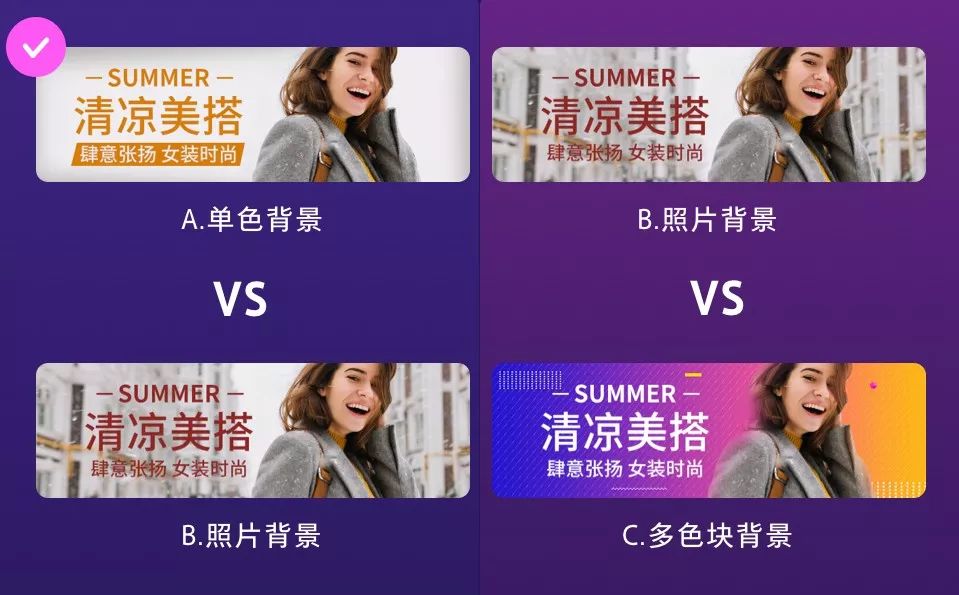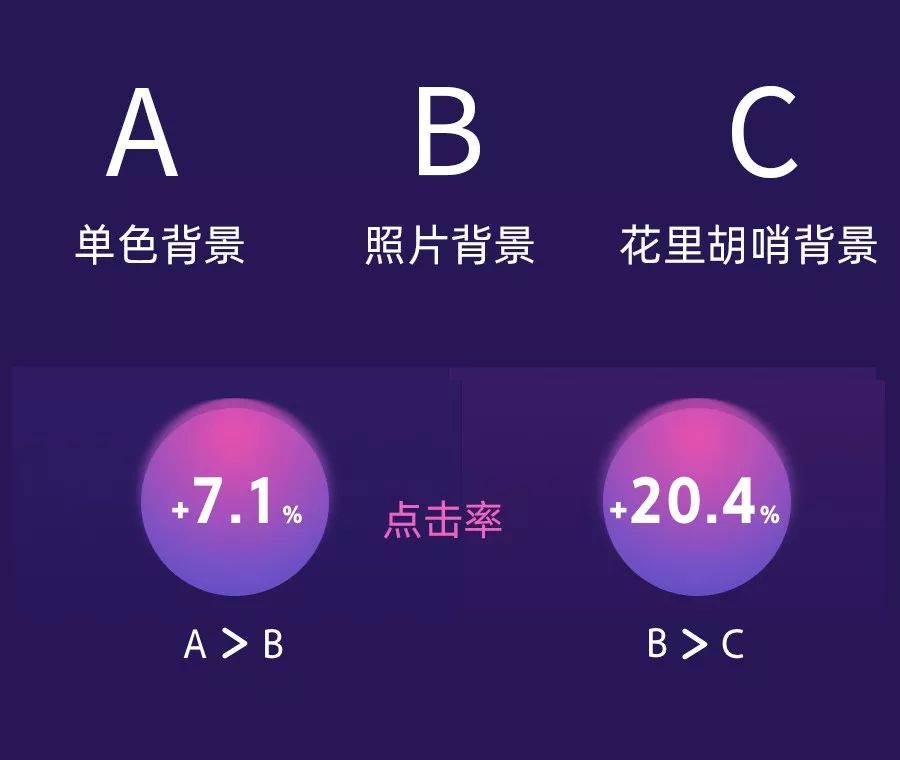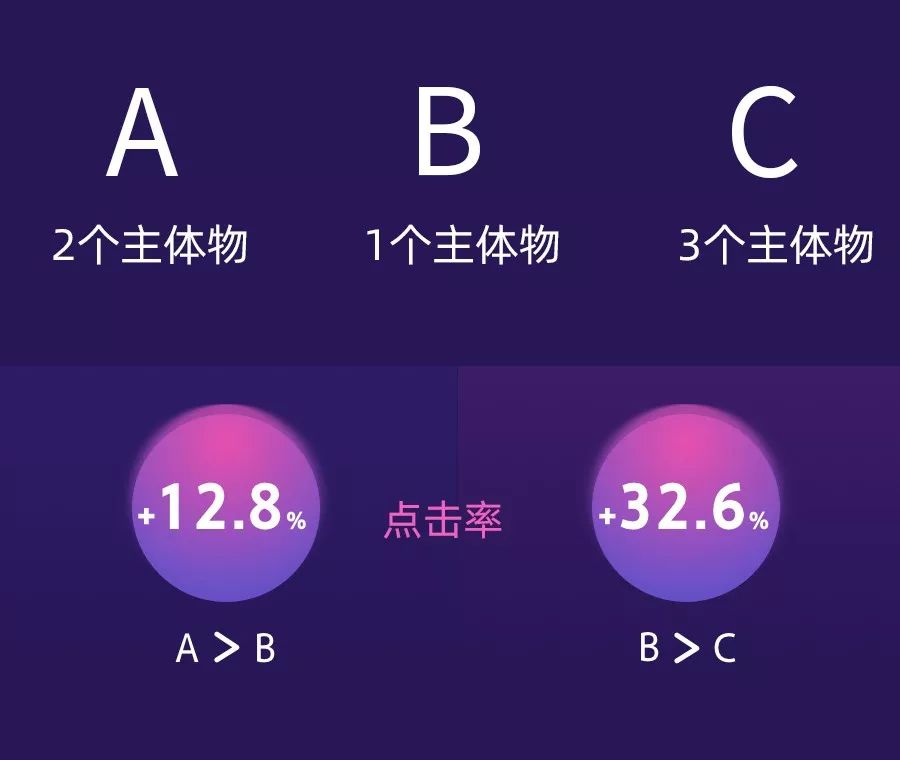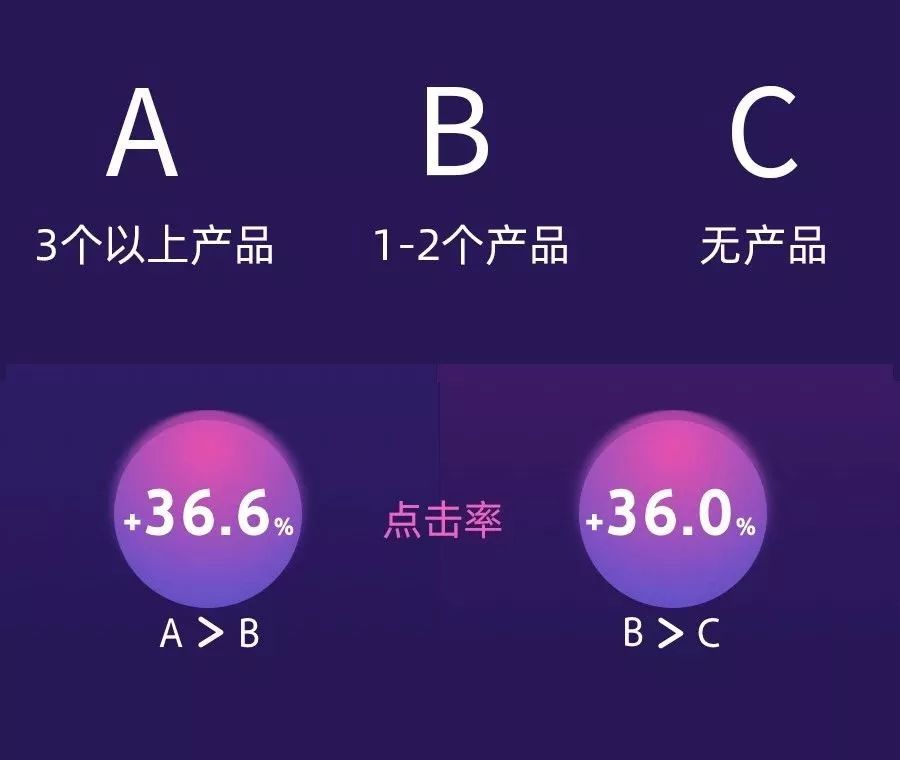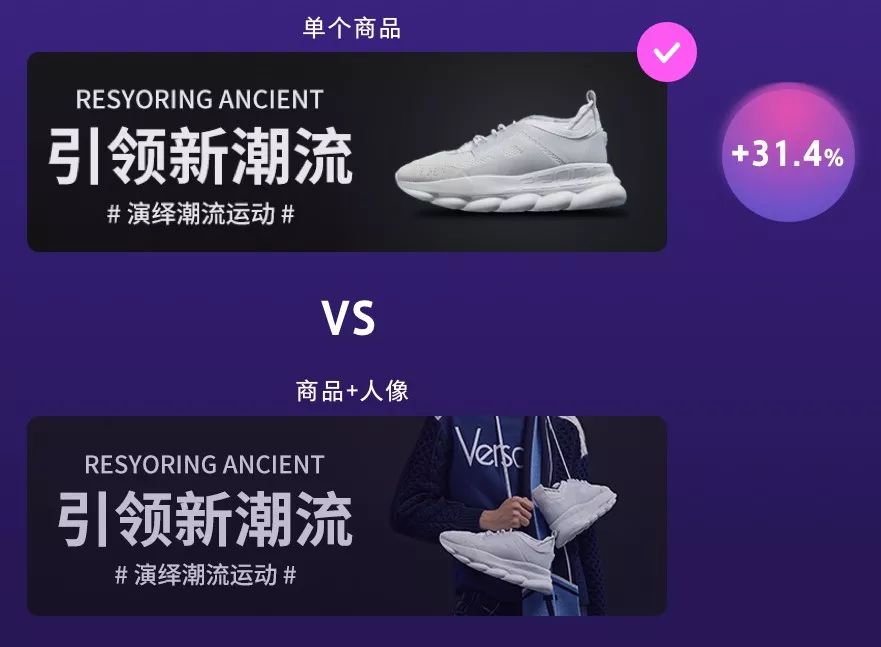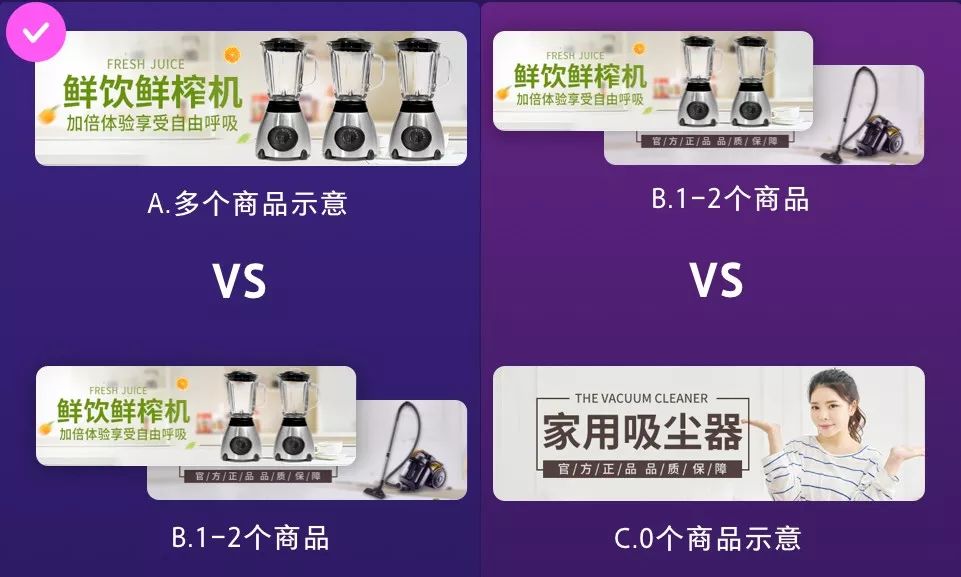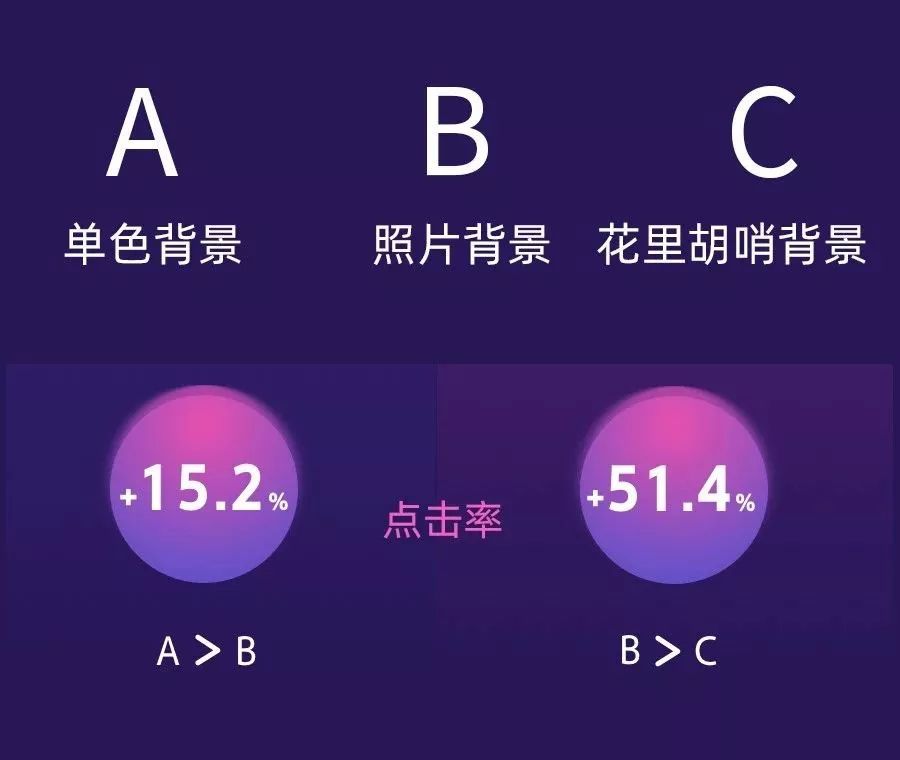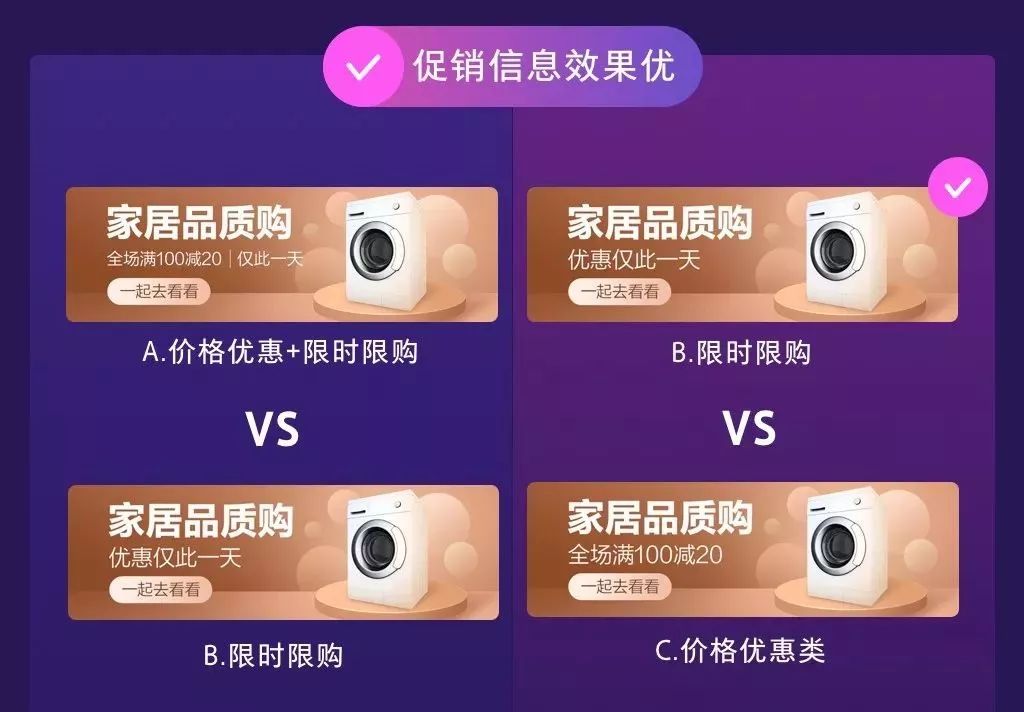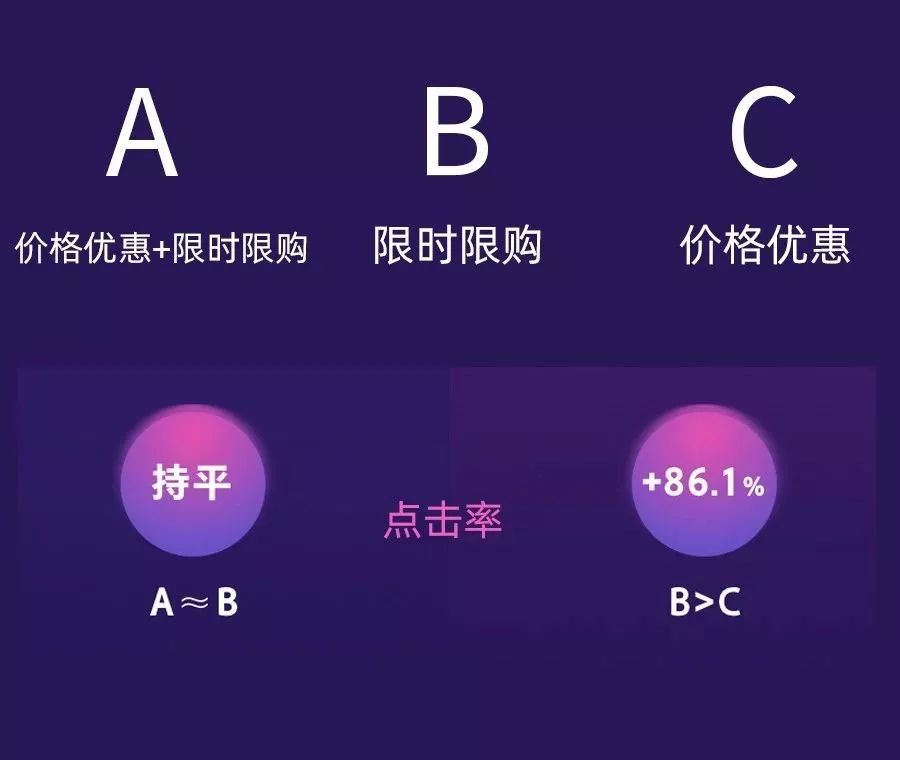
双十一箭在弦上,什么样的banner,最能“骗”人点击?
离双十一只有一周了,你的楼盖得怎么样了?省钱攻略又做好了吗?不过这都不要紧,毕竟计划赶不上变化,总有一些状态外的冲动加单,比如看见一个有欲望的banner……它为什么点击量最高?在阿里妈妈最新发布的权威报告中,都能得到解答。对于女装而言,单色背景的A点击率最高,因为简约的气氛,可以提升品质感,同时也可以凸显产品自身。照片效果的B仅次于A,而多色块的C就更低了,说明女装行业的背景越简单越好。
再深入一点,什么单色的点击率最高呢?并不是印象中的大红、黄、橙等醒目扎眼的颜色,而是白色、粉色这类具有女性柔美倾向的颜色。其中,粉色比非粉色,点击率提高45.2%,看来女人天生就是喜欢粉色萌萌哒!选好了主色调,还要定画面的元素,女装类目比较特殊,模特往往与商品直接绑定一起。但其实从数据上看,只含商品的banner要比商品+模特的创意,点击率高出28.8%,也就是说,你可以放大局部,突出产品,不要让模特喧宾夺主。
如果是展示商品+模特,一定要注意数量,2个最好,其次1个,3个就多了,效果不好。
运动和女装差不多,单色背景产品展示空间较大,点击率最高,照片场景其次,花里胡哨多色背景最低。
颜色选择跟女装也类似,高饱和度的依然不友好,不利于突出产品,中性的灰色调点击最高,可以涵盖不同年龄层。
没错,运动品类也喜欢纯商品的展示,可以突出产品细节,如果确实要放模特,建议只放一个,并且以衬托产品为主,或为其代言人。
最后还有一个小绝招,运动类目能放logo就放,不管是品牌logo,还是活动logo,看起来都更有吸引力,点击率要高。
从电器整体数据来看,棕色系背景的点击率最好,比其他颜色高出52.7%,黄色系背景最差,比其他低出43.6%,千万别踩雷。而一些饱和度较高的红、粉,以及大众认为的科技感较强的黑色,点击率都欠佳。
都第三个类目了,还是突出产品的点击最高,感觉模特费都省了。因为是家用电器,你可以展示3个以上产品,既有一定视觉冲击力,同时又有大促气氛。但如果是高端品牌,还是要兼顾形象,谨慎使用多产品排版。
促销文案对电器类的点击提升是最直观的,一般有两种,一是价格优惠,你可以同时放,不过对效果提升并没有显著帮助,也可以单放一种,限时限量比价格优惠高86.1%。
居家就是要给人一种舒服的感觉,所以浅色背景最佳,特别是白色,比非白色效果提升13.1%。而紫色(降低42.5%)等高饱和度颜色点击偏低,因为过于抢眼,直接弱化了产品自身。居家类目很难将商品和模特结合在一起(感觉怪怪的),所以要么是纯商品展示,3组以上效果更佳,要么是明星代言人展示,会比有商品的点击高出24.5%。跟运动一样,有品牌或活动logo的,比不加任何logo的图片,点击提升10.4%,其中品牌logo的提升更明显,效果增长13.8%,说明用户对品牌有依赖性。
本来到这里就happy ending了,但柚子觉得有必要补充一下点睛的字体(套路一下)。借一句歌词就是,有的字说不出哪里好,但就是谁都替代不了,比如下面这两组。
没换之前,是“一汪死水”,换了以后,立马觉得画面都有灵魂了。
2、运动:简约且突出产品细节最好,配上活动logo更佳。3、电器:高客单电器强调产品自身及功能最佳,或通过堆砌产品,配合文案,打造大促气氛。4、居家:温馨的氛围,加上多款产品展示,效果最佳。用有影响力的代言人,也能增加吸引力,另外logo不能少。
5、字体:不同的字体,代表不同的营销点,提升点击量必备。